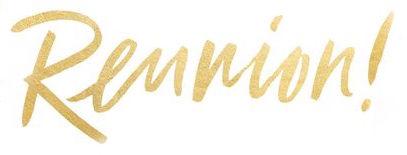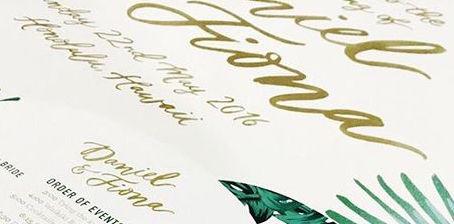
Welche Schriftarten sind das?
Ich suche diese Schriftarten oder ähnliche. Kann mir jemand weiterhelfen?
Da ich in all den dargestellten Texten kein n finde, das EXAKT einem anderen n gleicht, auch kein e, s, t oder r, nur um die am meisten vorhandenen Buchstaben zu nennen, sage ich mal, die Schrift "heißt" "nimm Tusche und einen Schreibpinsel, und schreibe"
sage ich mal, die Schrift "heißt" "nimm Tusche und einen Schreibpinsel, und schreibe"
Ist für den Anfang fast einfacher als irgendein Pinsel.
Ansonsten findet man derartige Schriften gerade zu Hauf – guck mal hier: